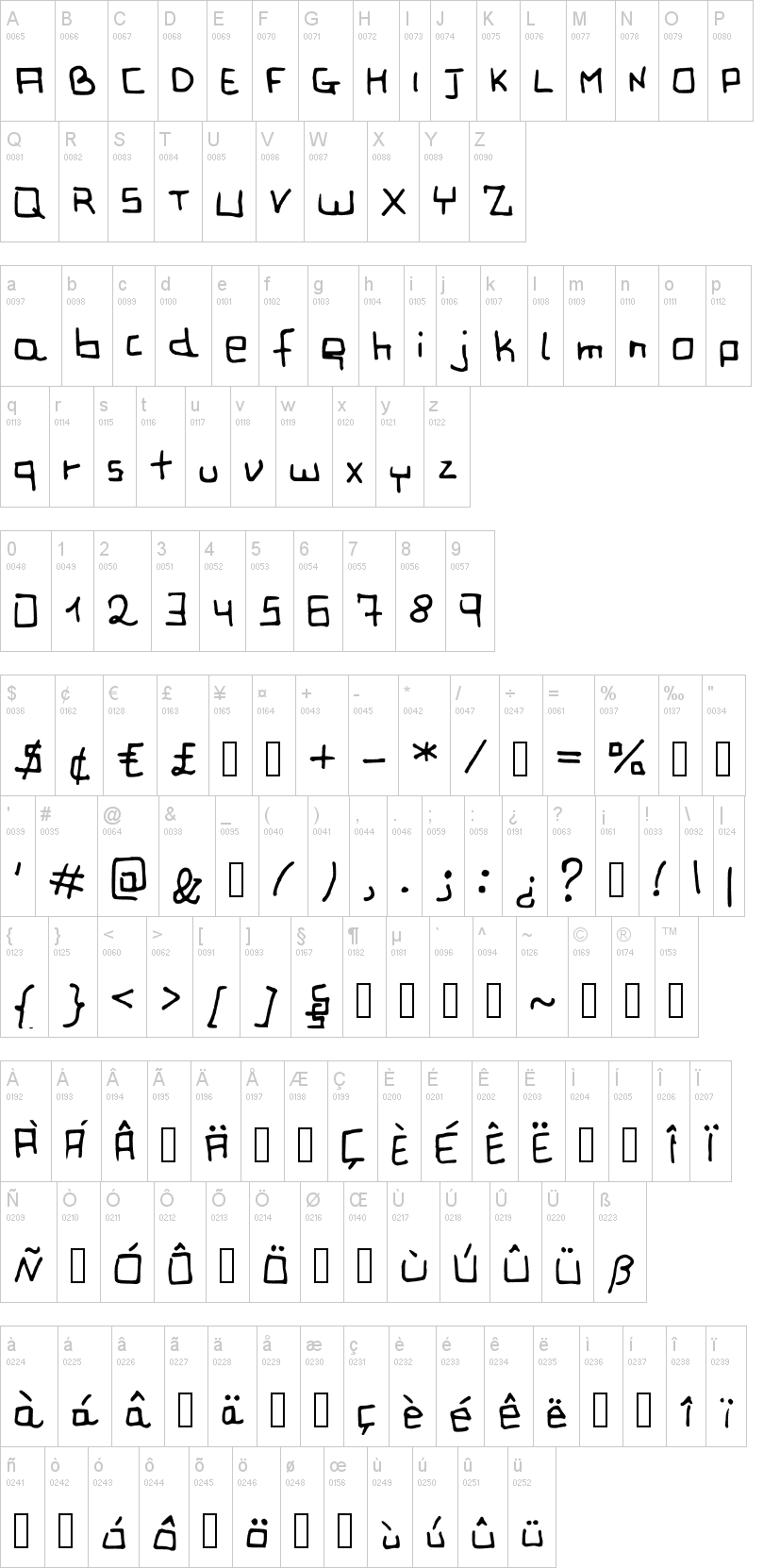
JD Vega 是一款由 Jack Usine 开发的独特粗体字体,它具有超大的字形,具有超强的可读性和表现力。JD Vega 的字形具有粗糙的线条,而且每个字母的字形都有着独特的细节,使其看起来十分有趣。它可以用于多种场合,例如品牌标志,海报,网页,书籍封面等。JD Vega 字体可以让你的设计看起来更加有趣,而且可以提升你的设计水平。内容介绍
JD Vega是一款非常不错的手写艺术字体,具有很好的视觉感,适合于文化类的宣传设计、商业类品牌的广告和产品包装设计以及个性化文字排版等较多场景。